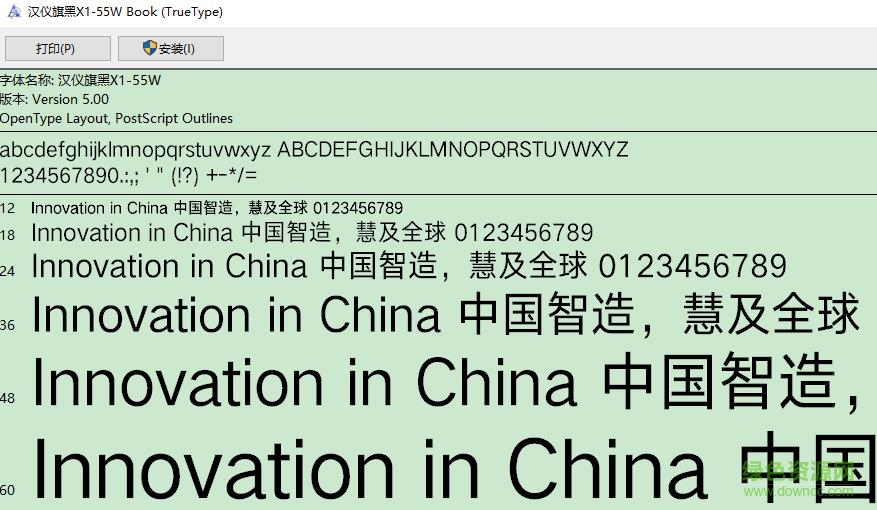
漢儀旗黑x1 55w是一款漢儀家族系列字體中的一款簡體中文字體,這款字體字形均稱大氣,字型樸素莊重,整體效果非常不錯,喜歡的朋友可以來綠色資源網(wǎng)免費下載使用!
結(jié)構(gòu)設(shè)計
UD設(shè)計盡可能減少多余的修飾元素,將除字形識別以外的信息量將至最低,盡可能避免過大的弧度為閱讀所帶來的不穩(wěn)定感,更方便視覺障礙者的閱讀。
西文設(shè)計
漢儀旗黑的西文設(shè)計沿用了與著名字體helvetica和Univers相同的Neo-grotesque字形風(fēng)格。Neo-grotesque類字形簡潔勻質(zhì)硬朗,可以與旗黑的中文部分達成非常良好的配合。
筆畫設(shè)計
設(shè)計簡約、爽朗富有時代氣息固然重要,但我們在設(shè)計時不能忘卻字的民族性和傳統(tǒng)文化,筆劃必須要有內(nèi)涵。筆畫設(shè)計中融入了書寫的韻味,采用“陰陽線”的處理方法,講究線條之美,使筆劃挺拔有力,剛?cè)嵯酀?。通過筆畫的粗細(xì)變化,賦予字體不同的性格與表現(xiàn)力,但“骨子里”卻是“一家人”,線條勁道,緊致。